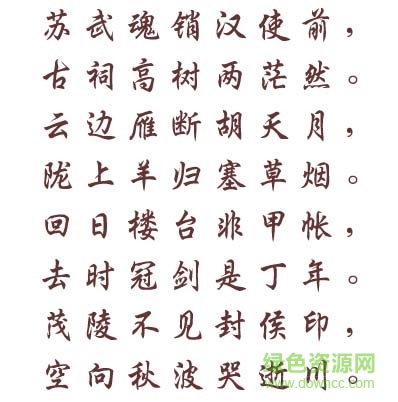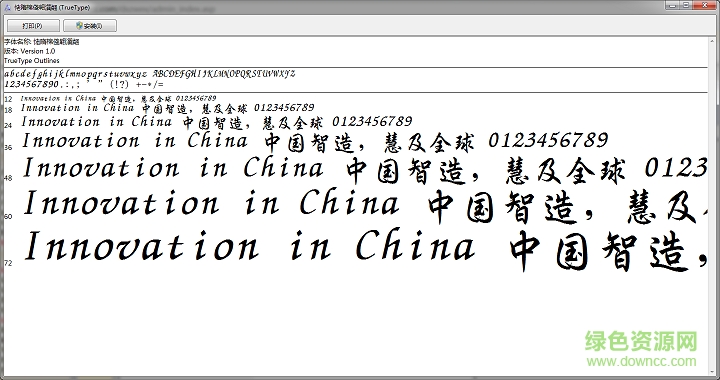
文鼎粗行楷簡字體
文鼎粗行楷簡吸收了行楷兩大字體的特點,呈現(xiàn)出了楷書的端莊,又有行書的凌厲,很有觀賞感。讓你在進行書面排版或者是各種廣告設(shè)計是更加有牌面,感興趣的朋友可以來本站下載體驗一下哦。
文鼎粗行楷簡字體特征
文鼎粗行楷有著行楷字體的共有特征,字體比較活潑,行楷字,也稱“漢字行楷手寫體字形”,是偏重于楷書書寫筆法(法則),比楷書行筆自由,又比行草規(guī)正的行書字體